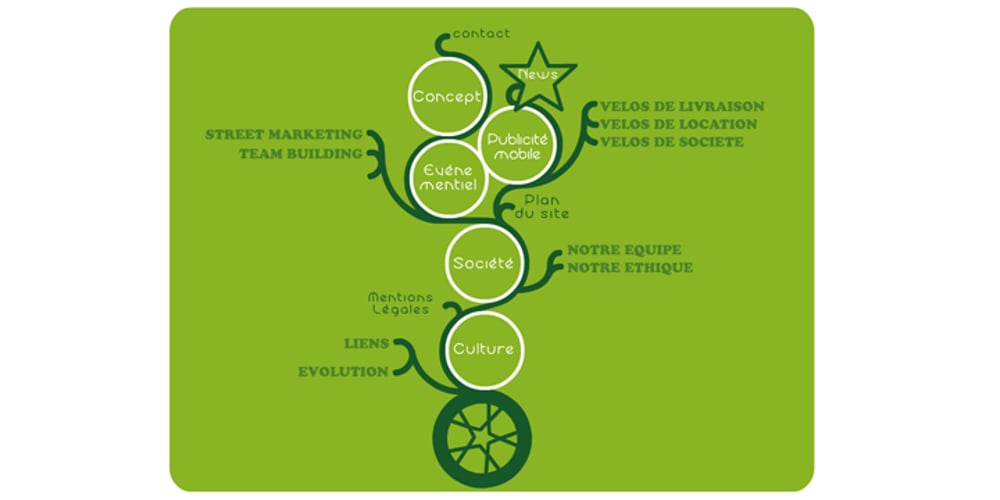
Cyclo
Cyclo font
Cyclo Font Family was designed by Florent Courtaigne and published by Cubo Fonts. Cyclo contains 13 styles and family package options. Ainsi que le considérait Geoffroy Tory, typographe et philosophe de la Renaissance, chaque lettre de l’alphabet peut être dessinée à partir d’un cercle et d’un trait. La fonte “cyclo” actualise et radicalise ce principe graphique visionnaire. Le pack contient une version “regular” assez sage et une version “alternate” plus fantaisiste dans les accents et des signes de ponctuation. La fonte cyclo est dont adaptée à tous les usages (titres, sous-titres, chapitres et blocs de text), et peut servir efficacement l’identité visuelle de votre projet.